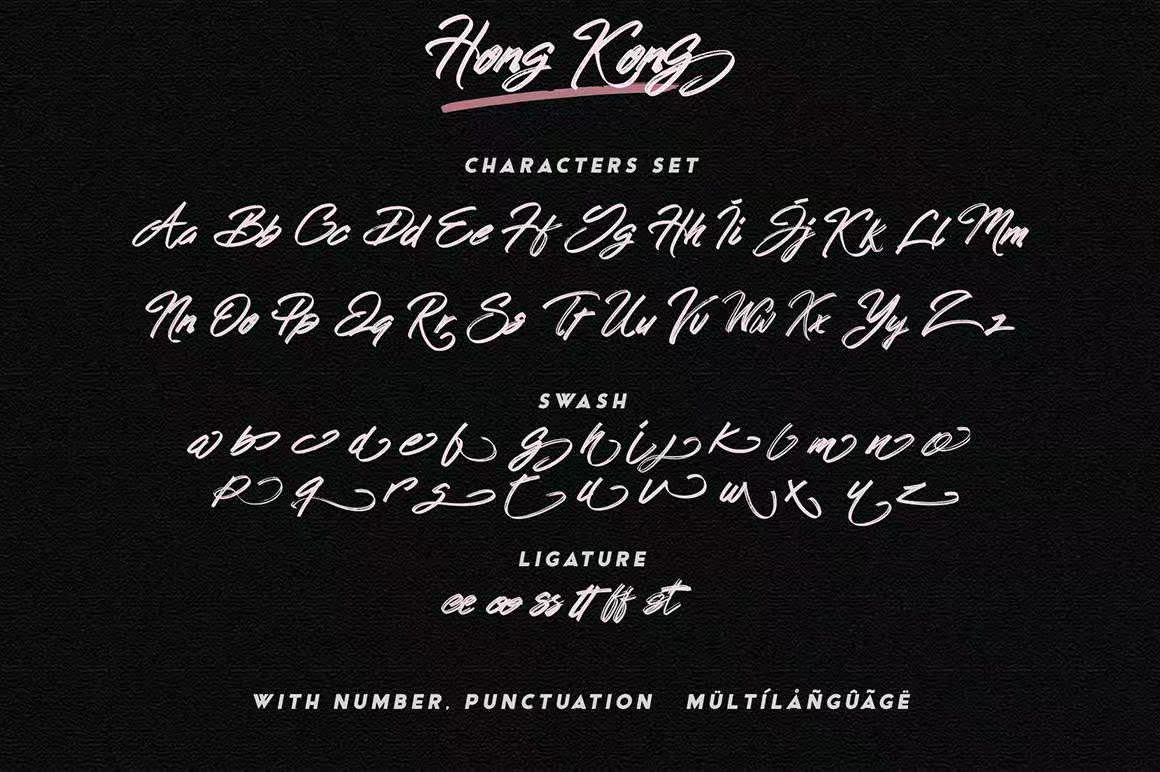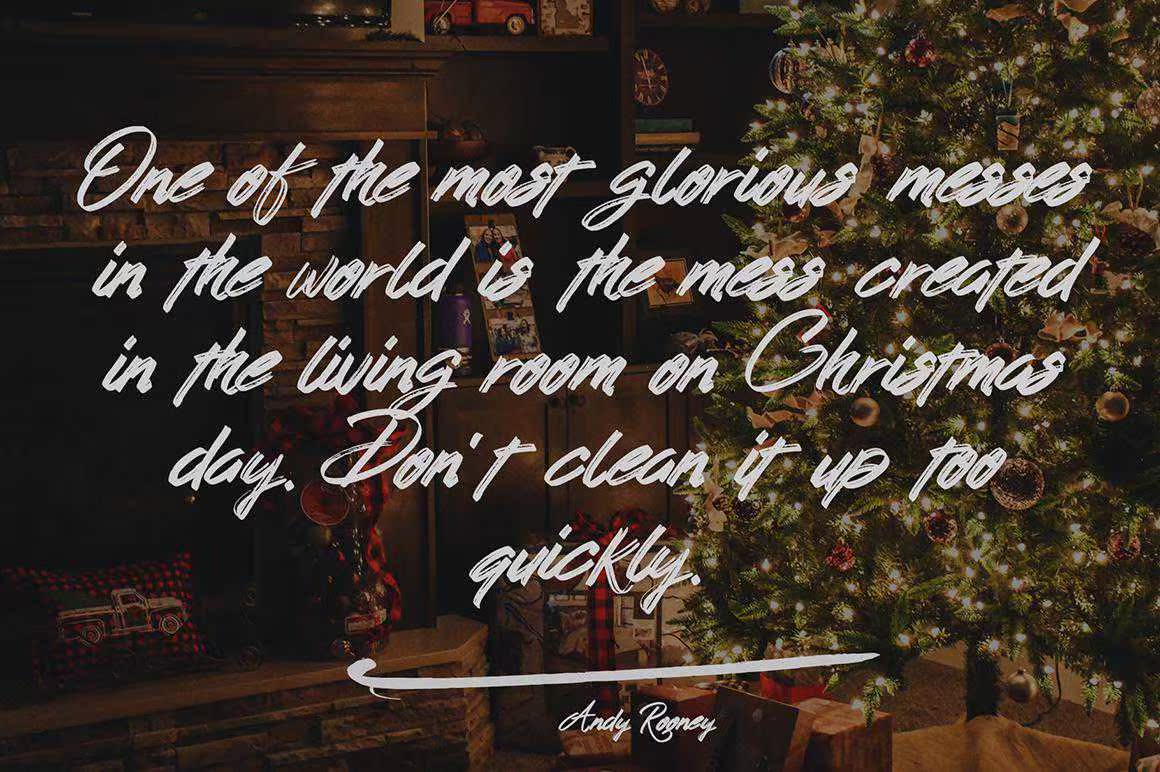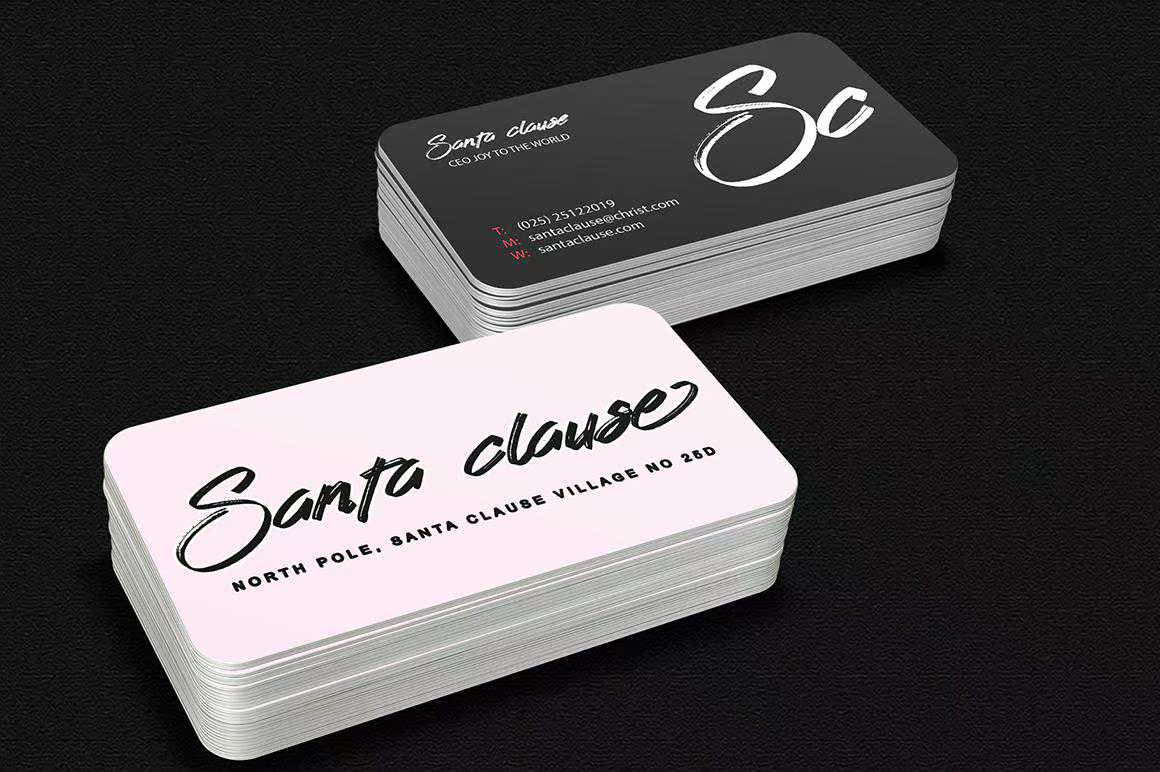
香港手写体是一种优雅而阳刚的字体。特别注意快速笔划和清晰的细节,香港手写体包含大写字母、小写字母和字母。这种字体可以在婚礼和圣诞节中使用。可以在杂志、服装、婚礼、书、t恤、连帽衫、报价、youtube、报价、产品包装、,网站或任何需要的东西。如果您有任何问题,请随时与我们联系! thomasaradea@gmail.comHongKongScriptBrushisaelegantandmasculinfont.withextraattentiontoquickstrokesandsharpdetails,hongkong contain suppercase,小写字母和小写字母。此字体适用于婚礼和圣诞节期间的缩略词。请在杂志、服装、婚礼、书籍、t恤、连帽衫、报价、youtube、报价、产品包装、,网站或任何需要的东西。如果您有任何问题,请随时与我们联系! thomasaradea@gmail.com